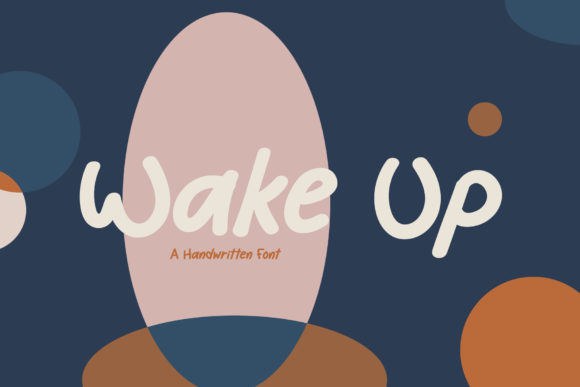
Wake Up
Si vous recherchez des ressources de haute qualité comme Wake Up, ce pack premium est un choix fantastique pour vos projets créatifs.
Que vous créiez des produits POD (impression à la demande), des invitations de mariage ou des visuels pour les réseaux sociaux, Wake Up est un choix idéal.